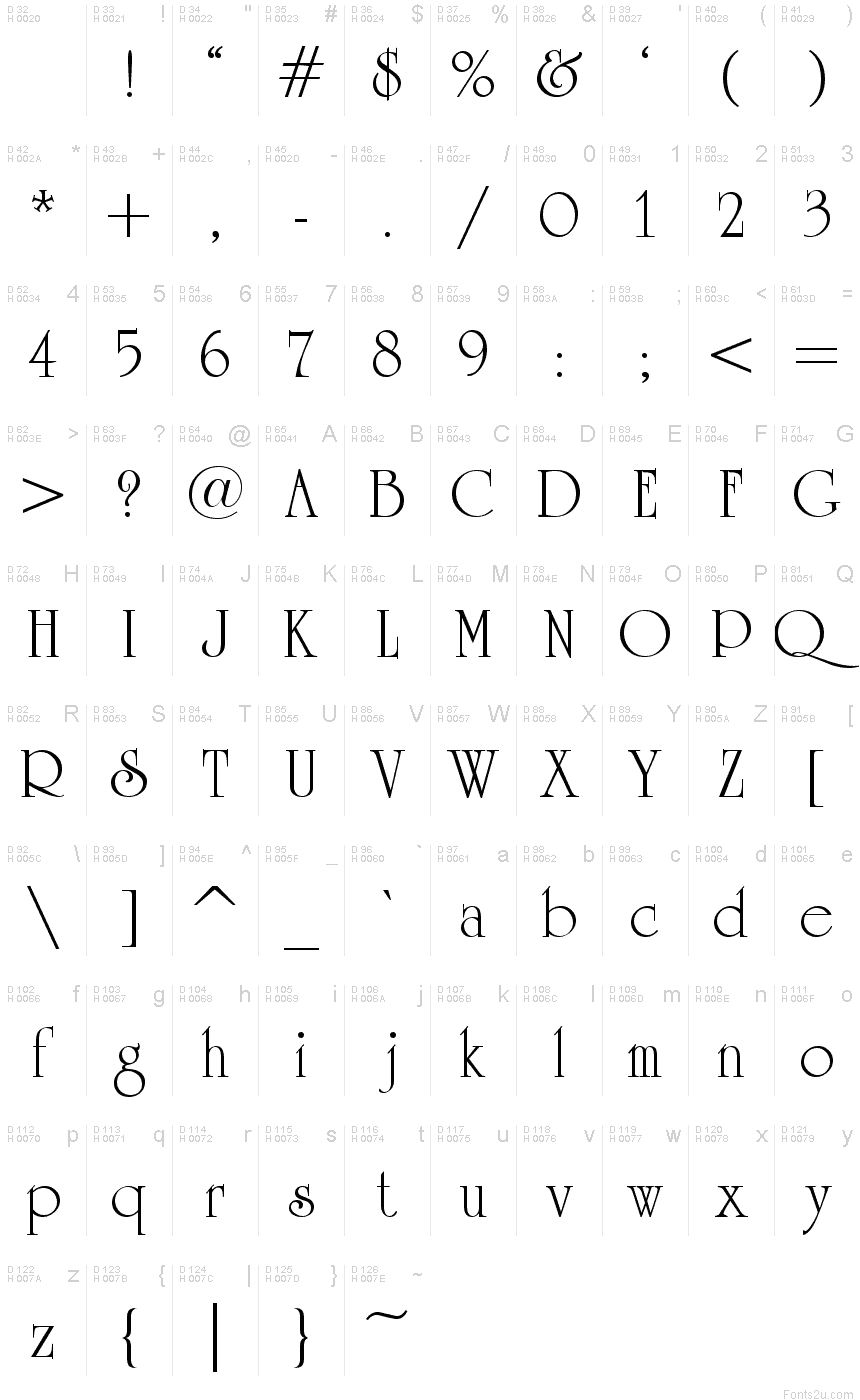
HawnUnivercity
Hawn Univercity od Guava Graphics to darmowy krój szeryfowy o wysokim kontraście, utrzymany w lekko literackim klimacie edytorskim późnego XX wieku. Litery łączą cienkie włosowate linie z pełniejszymi pionowymi pociągnięciami, a zaokrąglone małe litery sprawiają, że kontrast nie wydaje się surowy, dzięki czemu krój sprawia wrażenie wyważonego, a nie sztywnego.
Świetnie pasuje do okładek książek, nagłówków magazynów, opakowań typu boutique, menu restauracyjnych czy wyszukanych zaproszeń, gdzie darmowy font z tak wyrafinowanym kontrastem pozwala z gracją układać krótkie linie tekstu. Wykorzystaj go do okładek, tytułów czy inicjałów w stylu monogramu, zwłaszcza gdy szukasz klasycznego szeryfowego brzmienia z odrobiną dramatyzmu w krzywiznach.